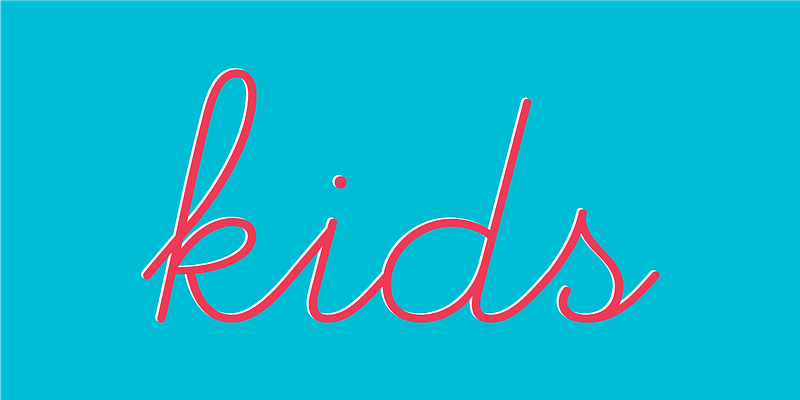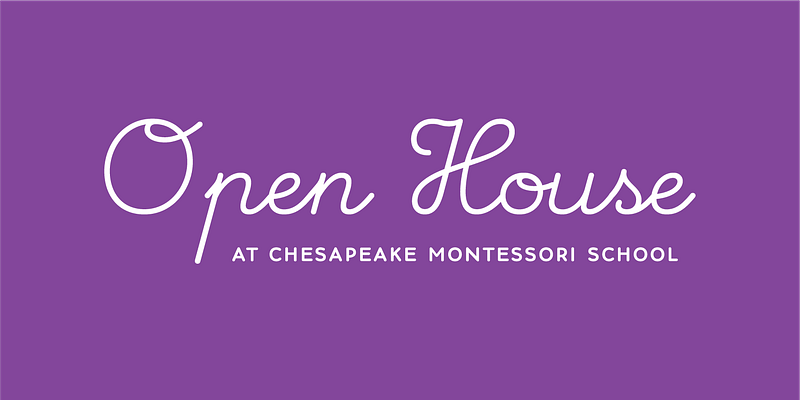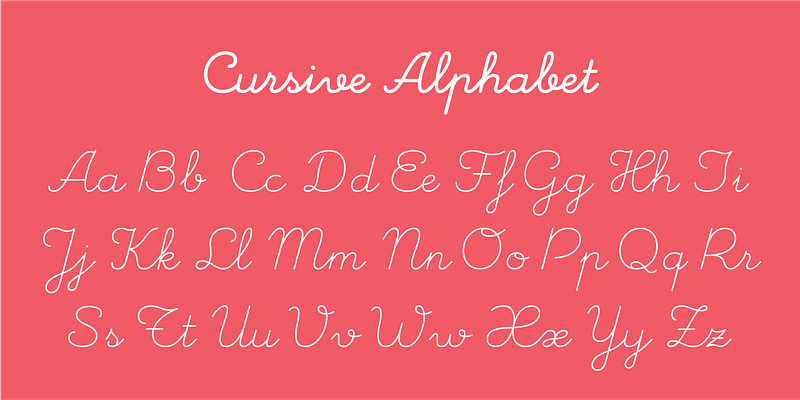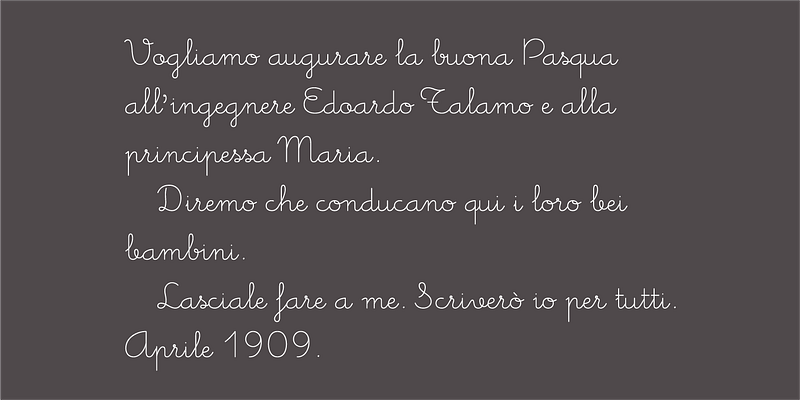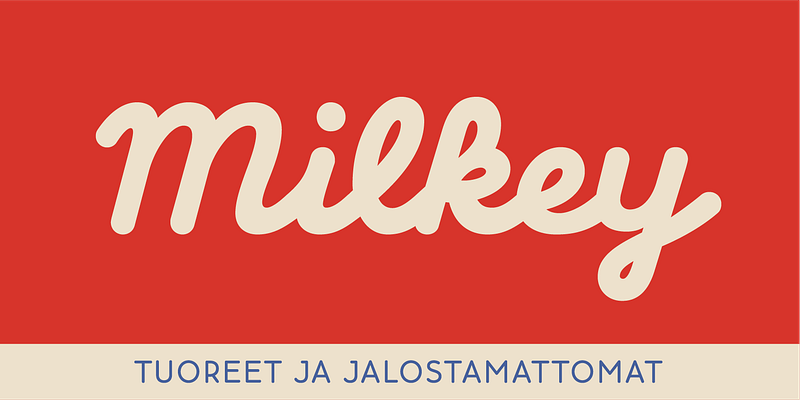
Memimas no es solo un afectuoso recuerdo de los días de primaria, sino también la primera tipografía personalizada de Type-Ø-Tones que encargó originalmente la editorial barcelonesa Barcanova en 1991. José Manuel Urós diseñó este estilo de letra para que se usara en una serie de libros para niños; desde entonces, esta tipografía ha evolucionado hasta convertirse en una familia con cuatro grosores con su cursiva correspondiente y un polivalente conjunto de características que incluye mayúsculas alternativas, ligaduras, una amplia gama de números y caracteres alternativos contextuales que hacen que la composición tipográfica de este estilo de fuente sea muy sencilla. Type-Ø-Tones, 1991 - 2019